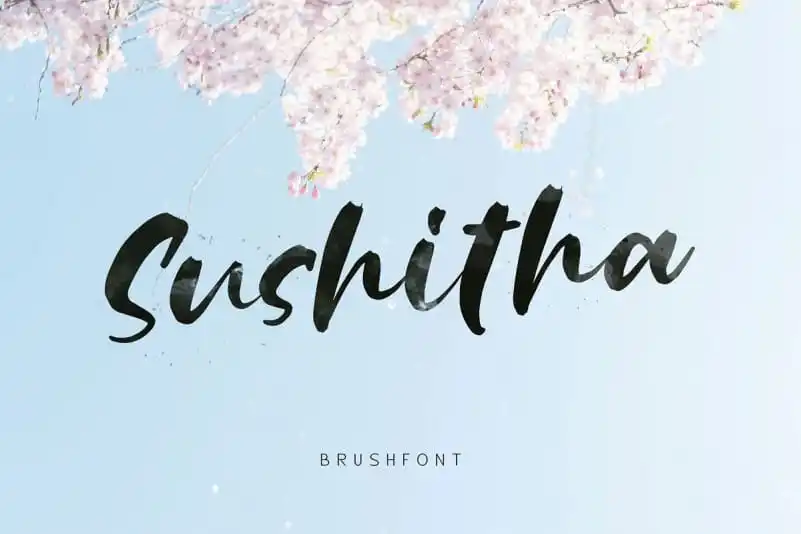
Sushitha Brush Font – Download Grátis
A Sushitha Brush Font é uma criação única que surge da interseção entre letras e traços feitos à mão com canetas-poster preenchidas com tinta negra. Ela nasceu de ideias experimentais, compartilhadas pela alit design em um ambiente onde o manualismo ganha força. Esta fonte é verdadeira a sua essência, preservando os movimentos de tração e resistência dos dedos sobre a caneta, resultando em linhas que variam da grossa à fina, criando uma impressão distintiva que se desvanece nas outras tipografias de script. A Sushitha é perfeita para conceitos de design que buscam um tom casual ou não-formal porque carrega a liberdade que surge do trabalho diário. Esperamos que você goste desta fonte, marcada pela sua personalidade e versatilidade no desenho.